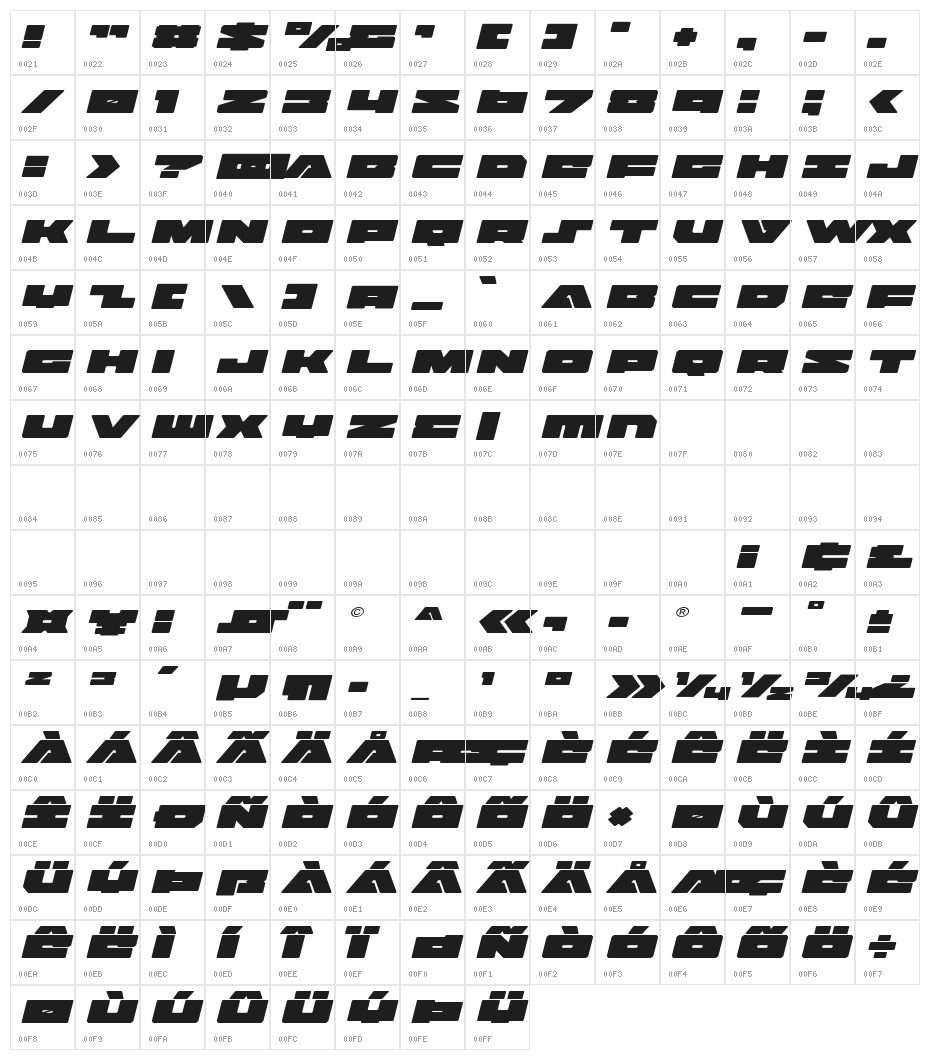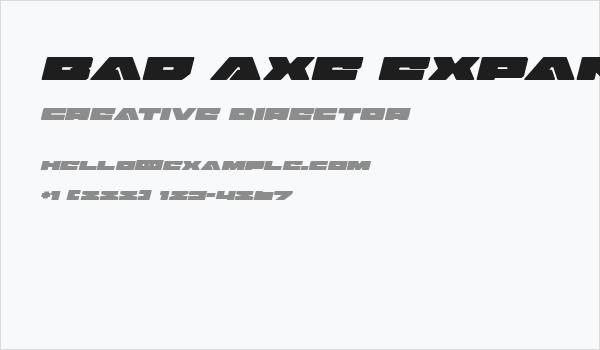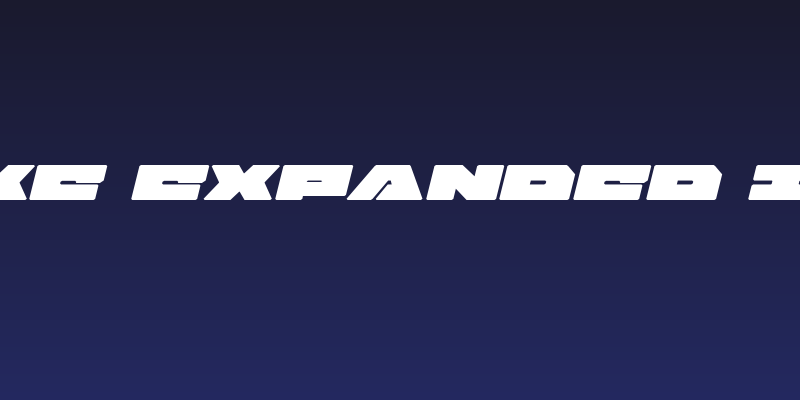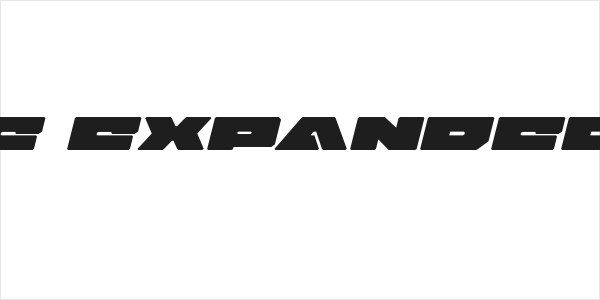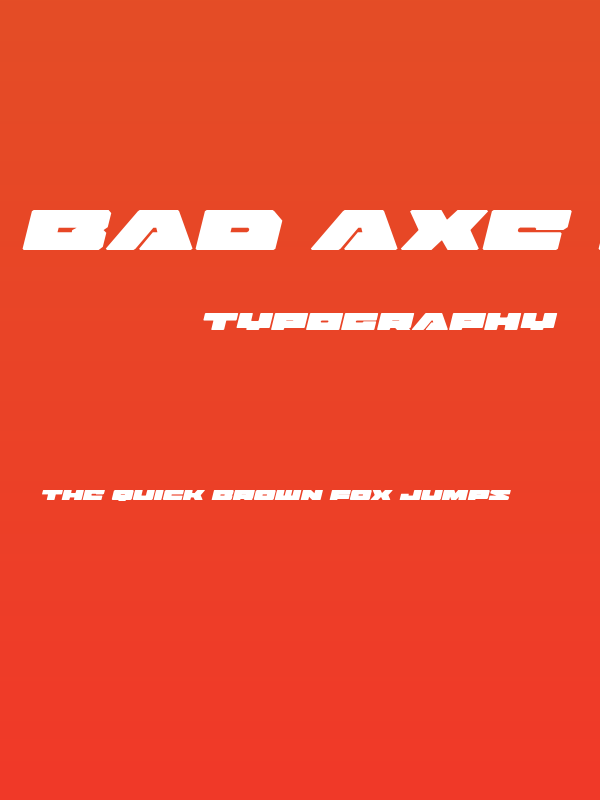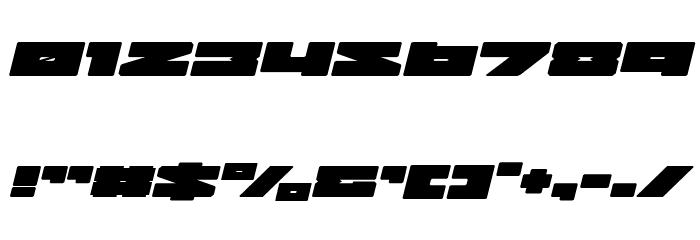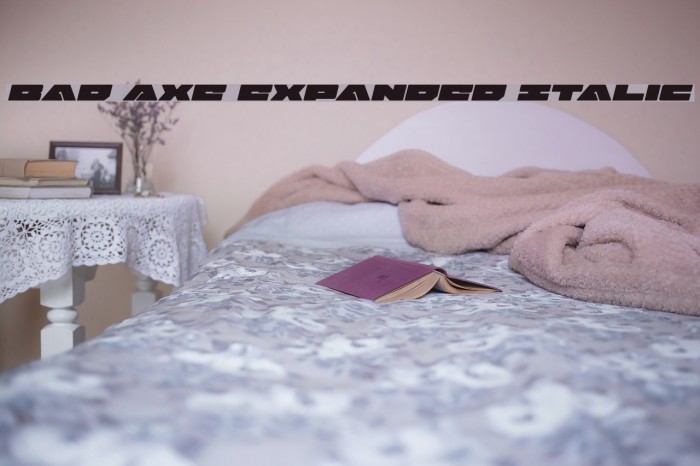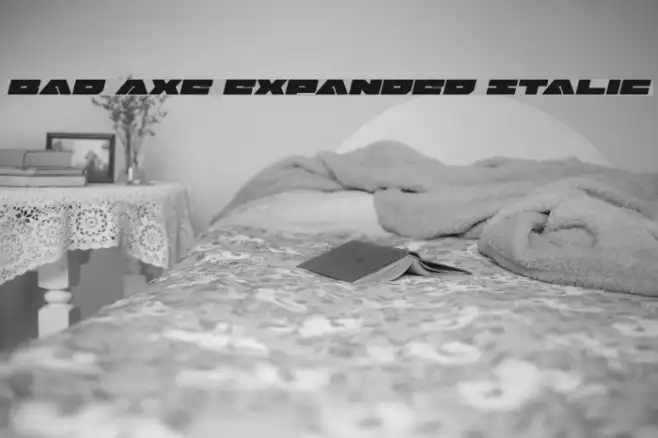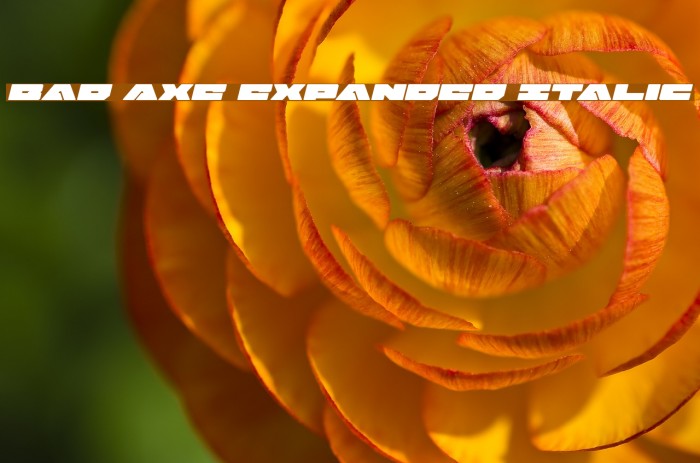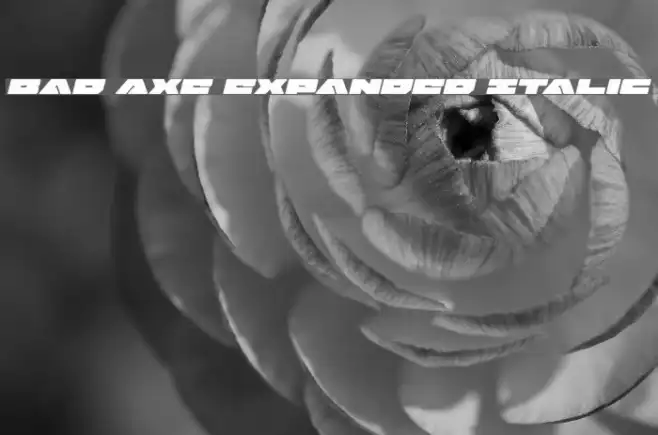
Bad Axe Expanded Italic Font
| Proyectos propuestos | Ideal for sci-fi themed designs, video game titles, posters, and branding that requires a strong, modern impact. |